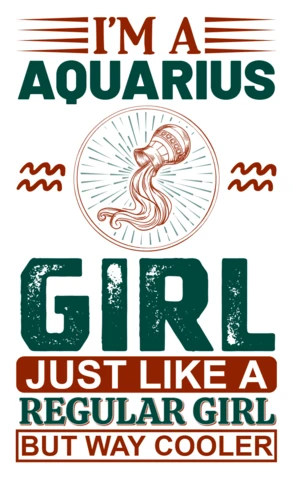
Modèle éditable de typographie de la fille Léo - style graphique amusant et audacieux
Éditer dans Design Studio Télécharger en JPGLibérez votre créativité avec notre modèle de design éditable sur le thème du Lion, parfait pour des vêtements et des marchandises audacieux qui célèbrent les anniversaires avec humour et avec une touche astrologique - amusant, graphique et inoubliable !